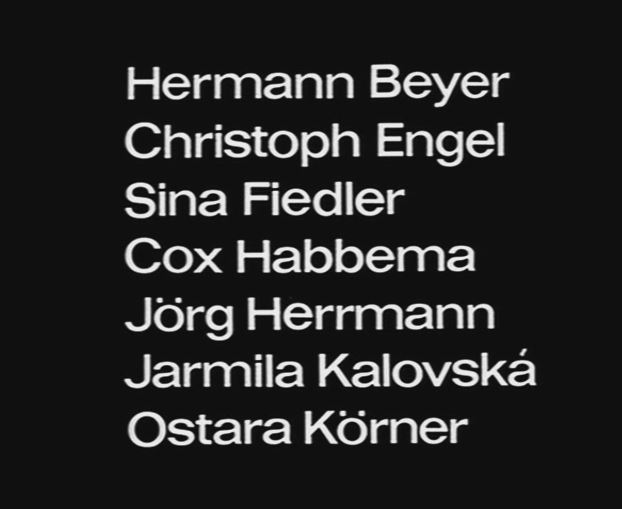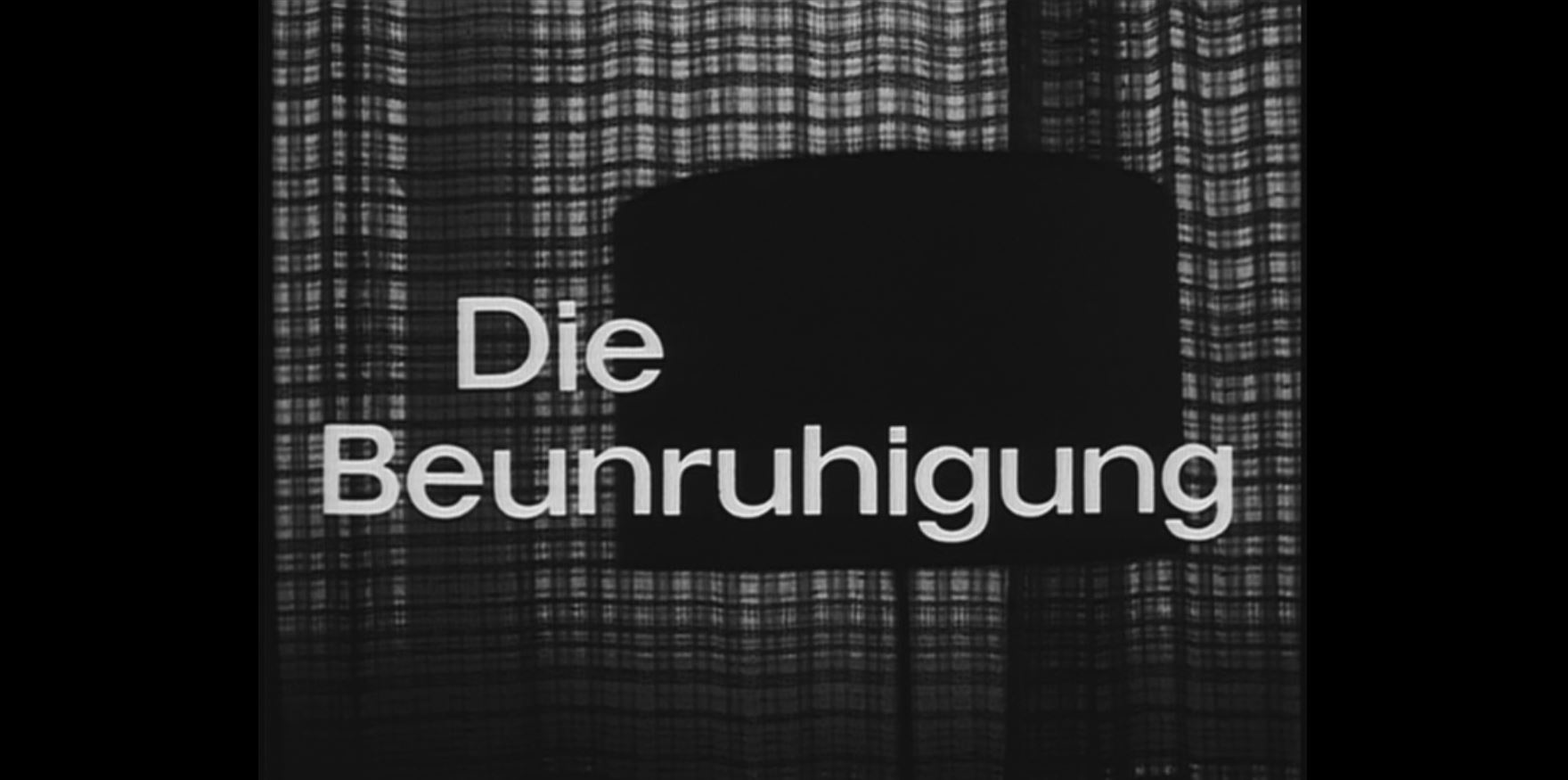
Schrift aus dem Vorspann eines Defa-Films
Der Film ist von 1981 und ich komme irgendwie nicht drauf … vielleicht ein leicht verzerrte Folio?
Folio und Helvetica würde ich nach einigen Recherchen ausschliessen. Auffällig sind die Punkte beim ö und die relativ geringe Höhe der Versalien ...
Nun, DEFA war ja die Filmgesellschaft der DDR, also würde ich hier auch eher auf eine Typoart-Schrift tippen. Mir kommt es vor, wie eine Maxima oder eine etwas gestreckte Akzidenz Grotesk. Müsste man noch mal genauer betrachten.
Akzidenz Grotesk würde ich ausschliessen - das kleine a sieht deutlich anders aus und die Punkte beim ö passen auch nicht.
Die Maxima ist es auch nicht - K, J und S sehen anders aus.
das es akzidenz nicht ist, ist klar — wie gesagt ...
ich denke das ist keine bestehende schrift sondern eher handgemacht (sieht man auch an der springenden x-höhe) und akzidenz oder folio und co. haben pate gestanden.
Die Permanent von Karlgeorg Hoefer für Ludwig & Mayer in Frankfurt ist am ähnlichsten. Die Permanent breithalbfett gab es für den Berthold Staromat. Die ist aber etwas kräftiger als die hier gezeigte Schrift. Die Differenzen könnten beim umkopieren entstanden sein. Wahrscheinlich handelt es sich hierbei aber um die Permanent breitmager. Beide Schnitte wurden 1963 veröffentlicht, könnte also hinkommen.